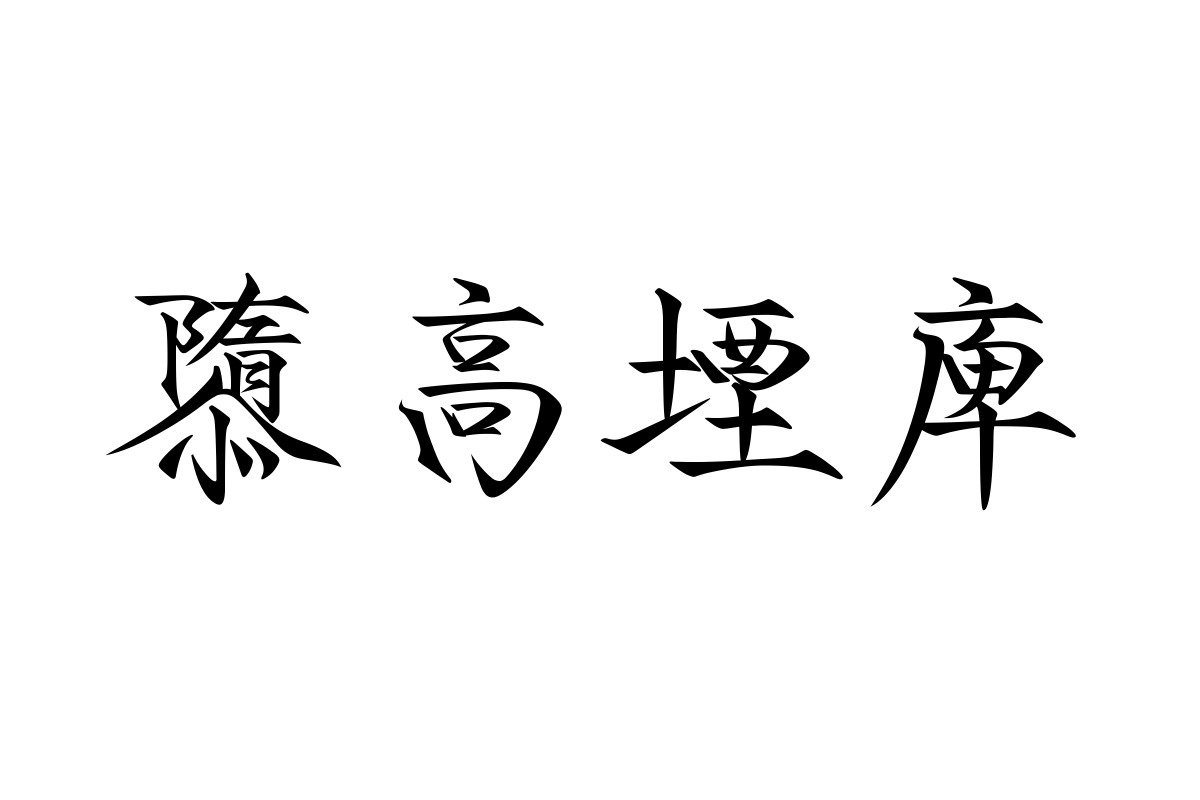
汉仪竹心楷是一款具有独特韵味的字体,它源自中国书法艺术的精髓。这款字体以竹子为灵感,将竹子的坚韧、挺拔和柔美融为一体,展现出独特的风格。
汉仪竹心楷的笔画流畅自然,线条优美,既有传统的韵味,又不失现代感。它的字形结构严谨,每个字都充满了力量和美感,让人一看就能感受到作者的用心和匠心。
此外,汉仪竹心楷还具有很高的识别度,无论是在印刷品还是电子屏幕上,都能清晰地展现其独特的魅力。它不仅适合用于书法作品的创作,也非常适合用于各类文字设计,如标题、正文、广告等。
总的来说,汉仪竹心楷是一款非常优秀的字体,它融合了传统与现代的元素,展现了独特的艺术魅力。无论是对于设计师还是书法爱好者来说,都是值得一试的好选择。